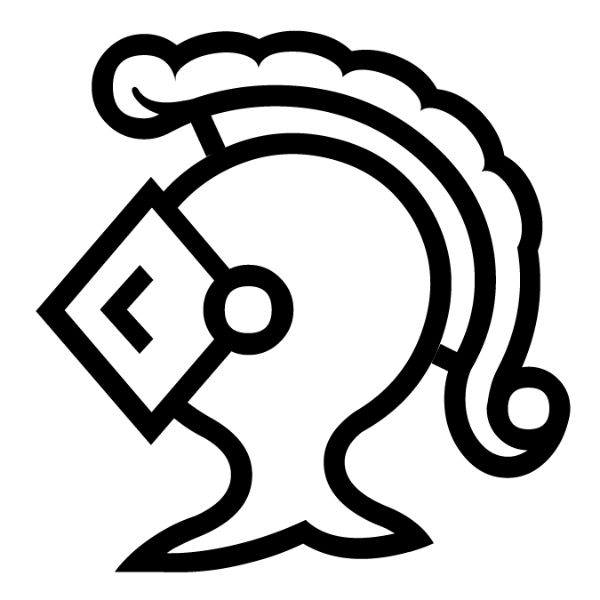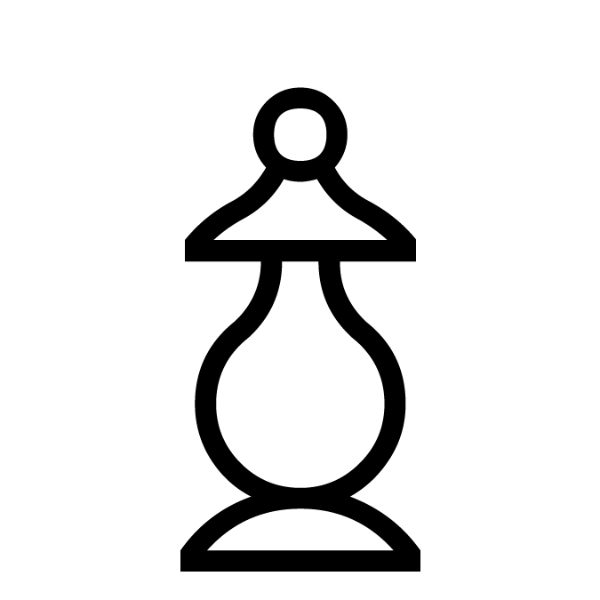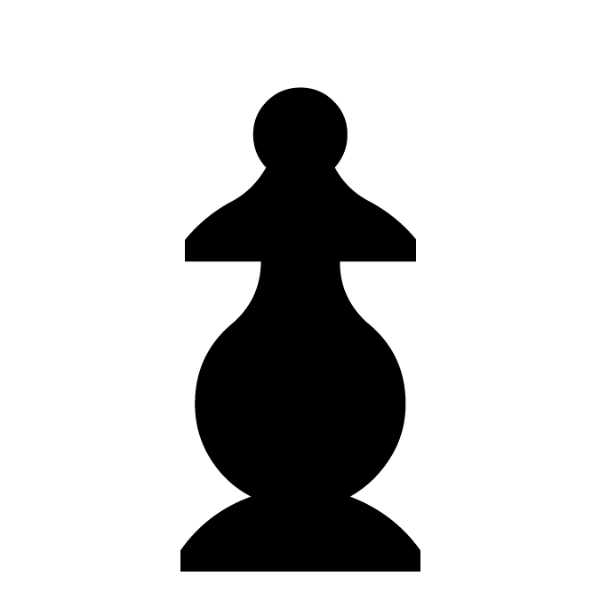
La fuente de ajedrez Chess Condal ofrece una combinación perfecta de elegancia y claridad. Es ideal para jugadores, entrenadores y diseñadores que desean añadir un toque clásico y estilizado a sus diagramas y proyectos de ajedrez. Chess Condal es una fuente de ajedrez gratuita, fácil de descargar e instalar, que mejorará la legibilidad y estética de cualquier presentación ajedrecística.